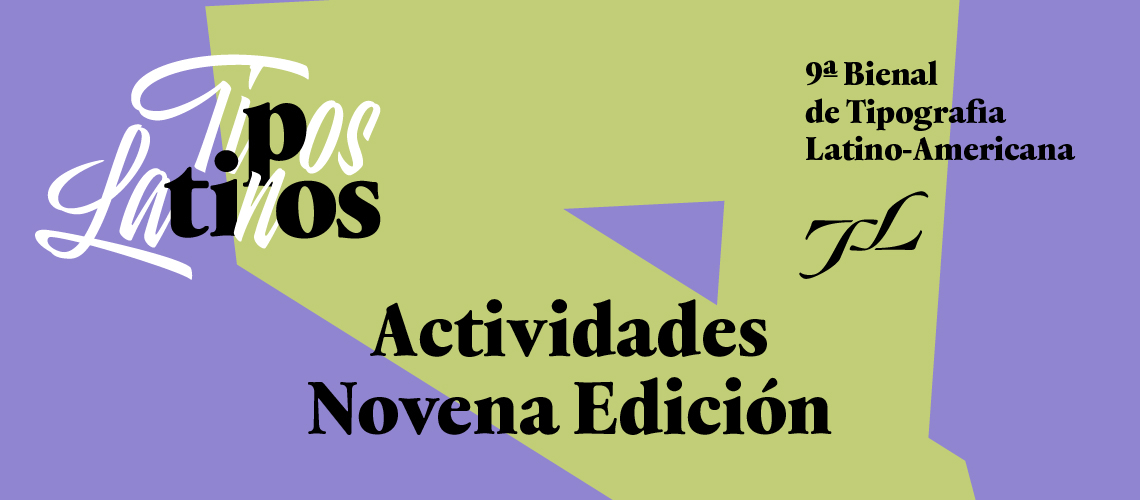
El trazo inicial: Taller de caligrafía
taller teórico / práctico de las bases caligráficas por Isabel Peña
Este taller de Caligrafía Fundacional se enfoca en las bases de la práctica caligráfica, necesarios para abordar cualquier estilo histórico y experimentar con los atributos de la letra.